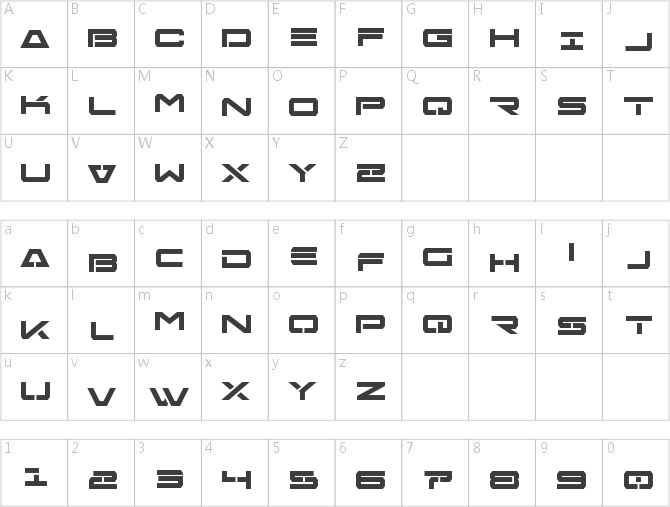
freeagentbold
freeagentbold介紹
freeagentbold字體字庫是一款讓人賞心悅目、百看不厭的英文字體,適合各類廣告和產(chǎn)品包裝設(shè)計(jì)應(yīng)用,字體大小0.02MB,格式為ttf字體,上傳用戶是哼哼哈兮,作者/版權(quán)方為未知